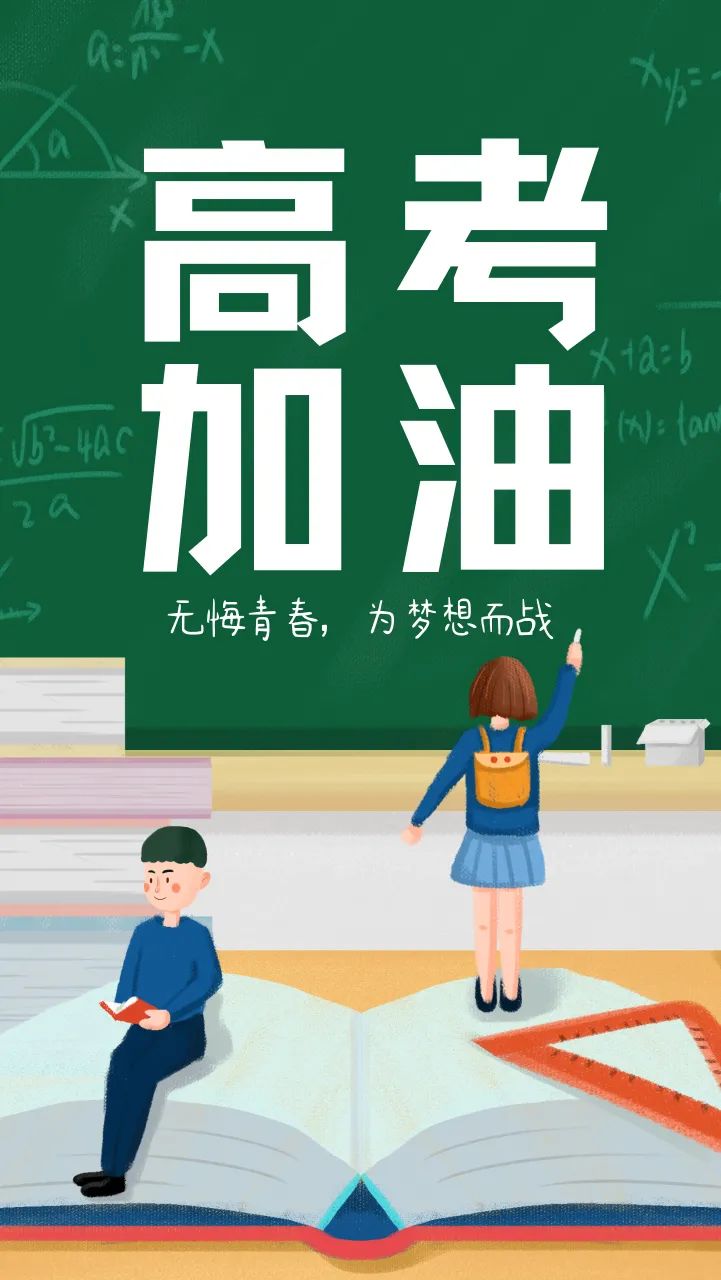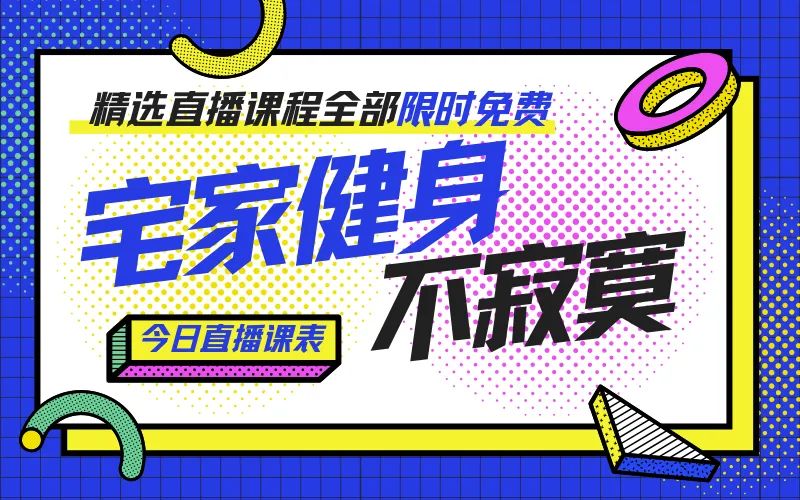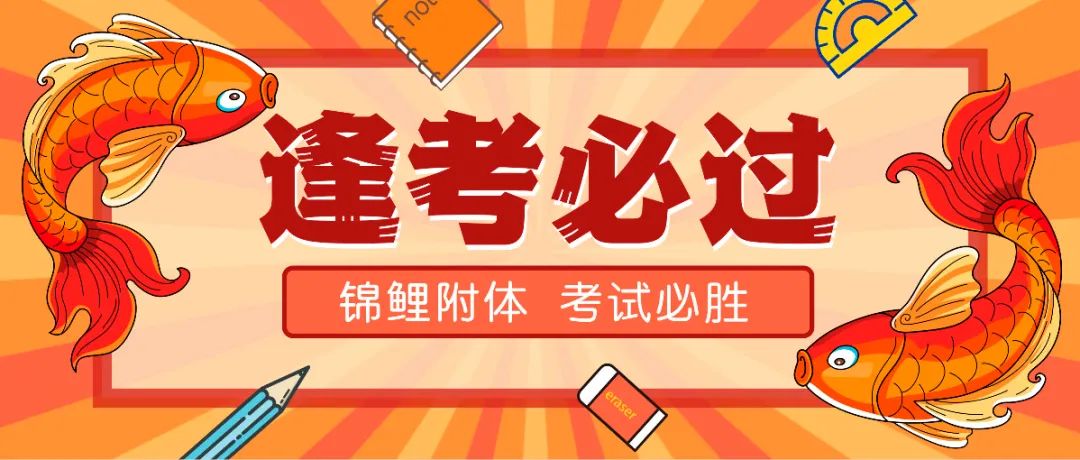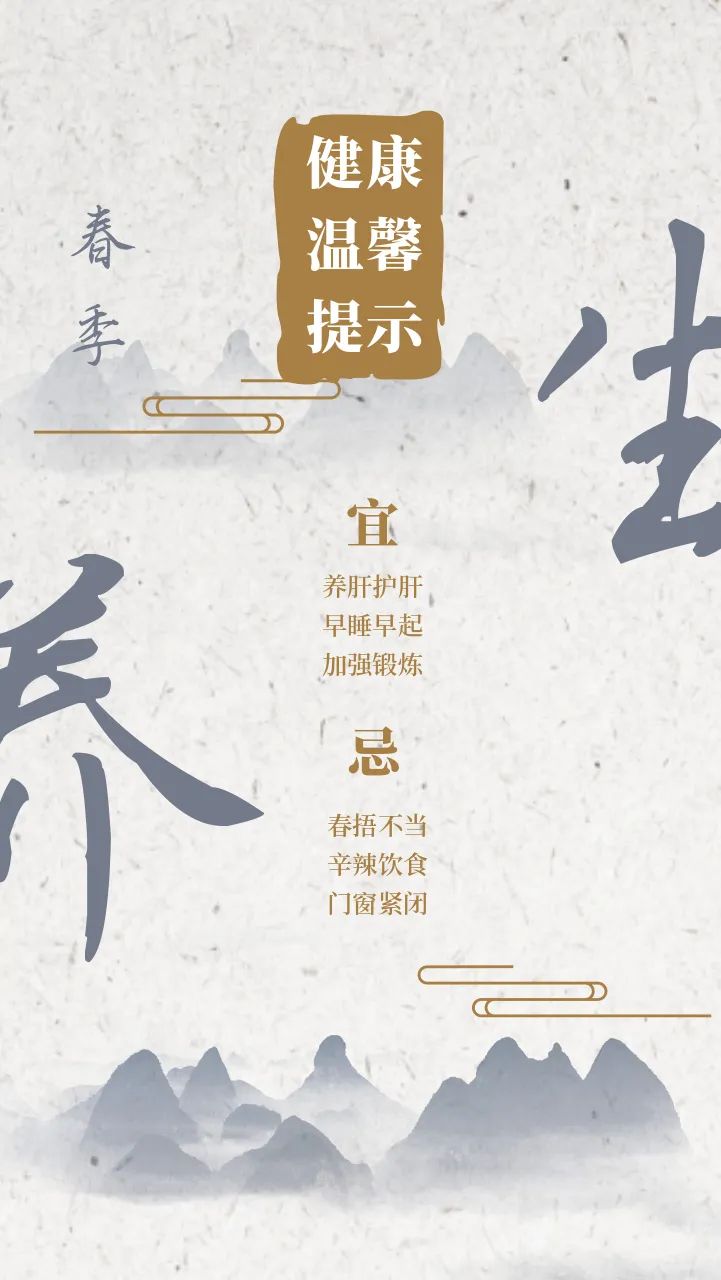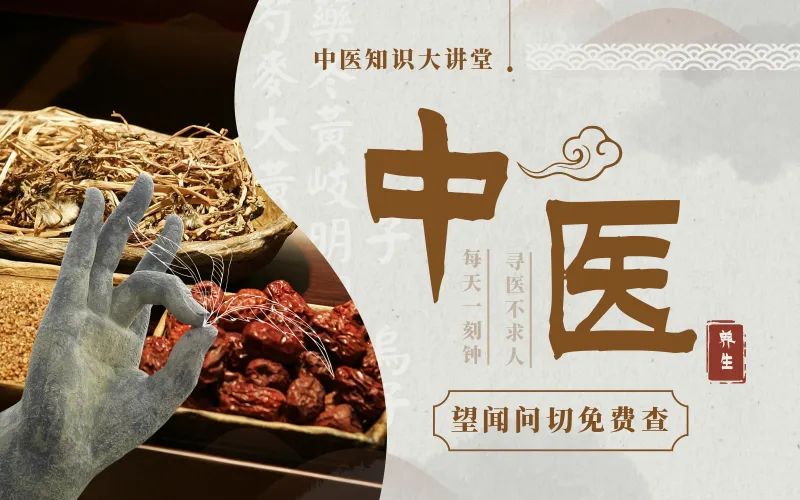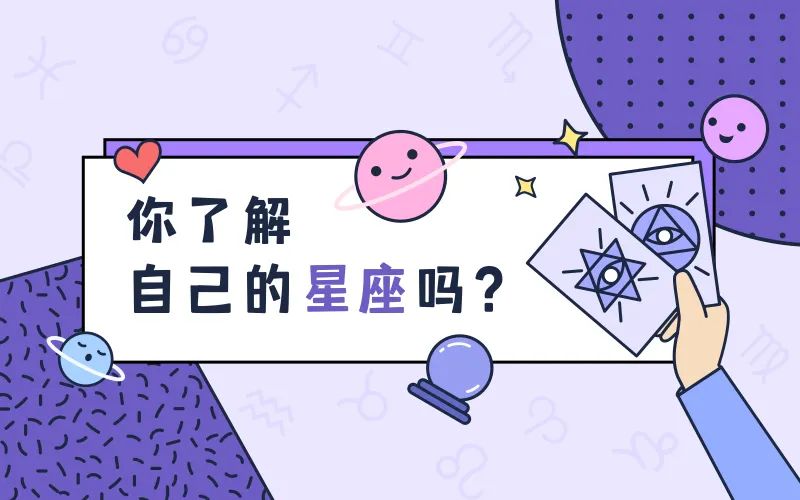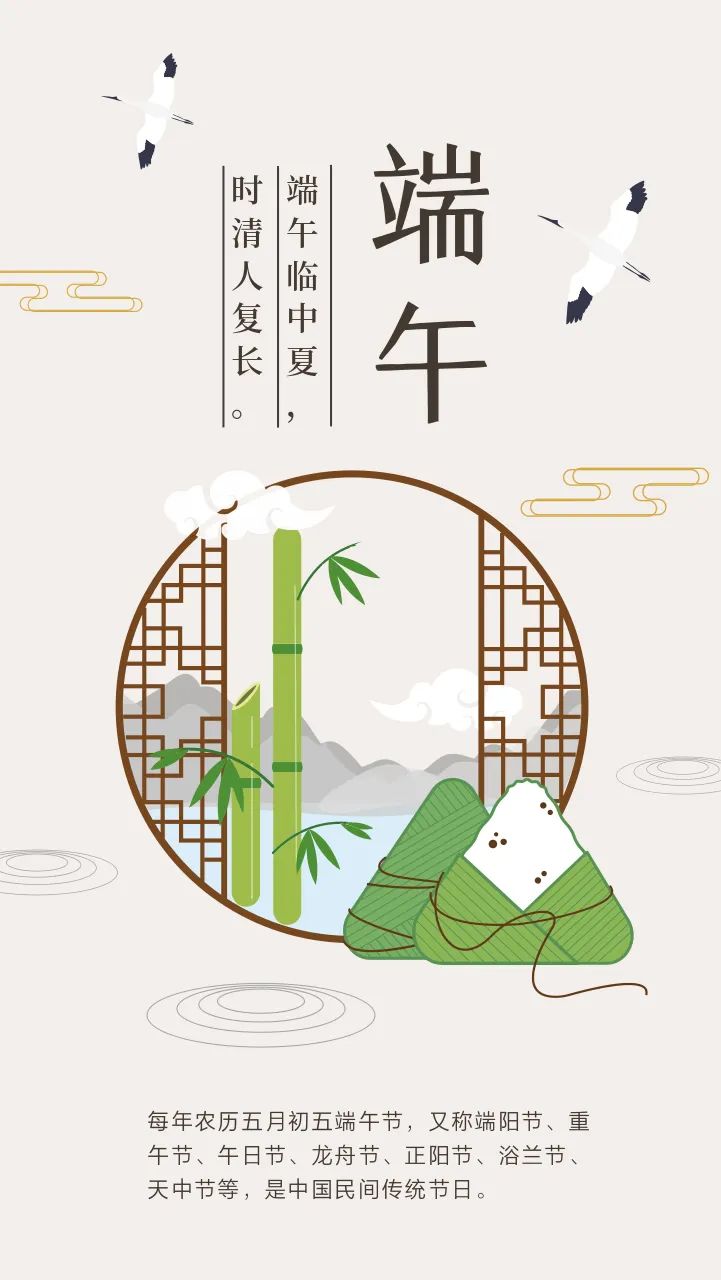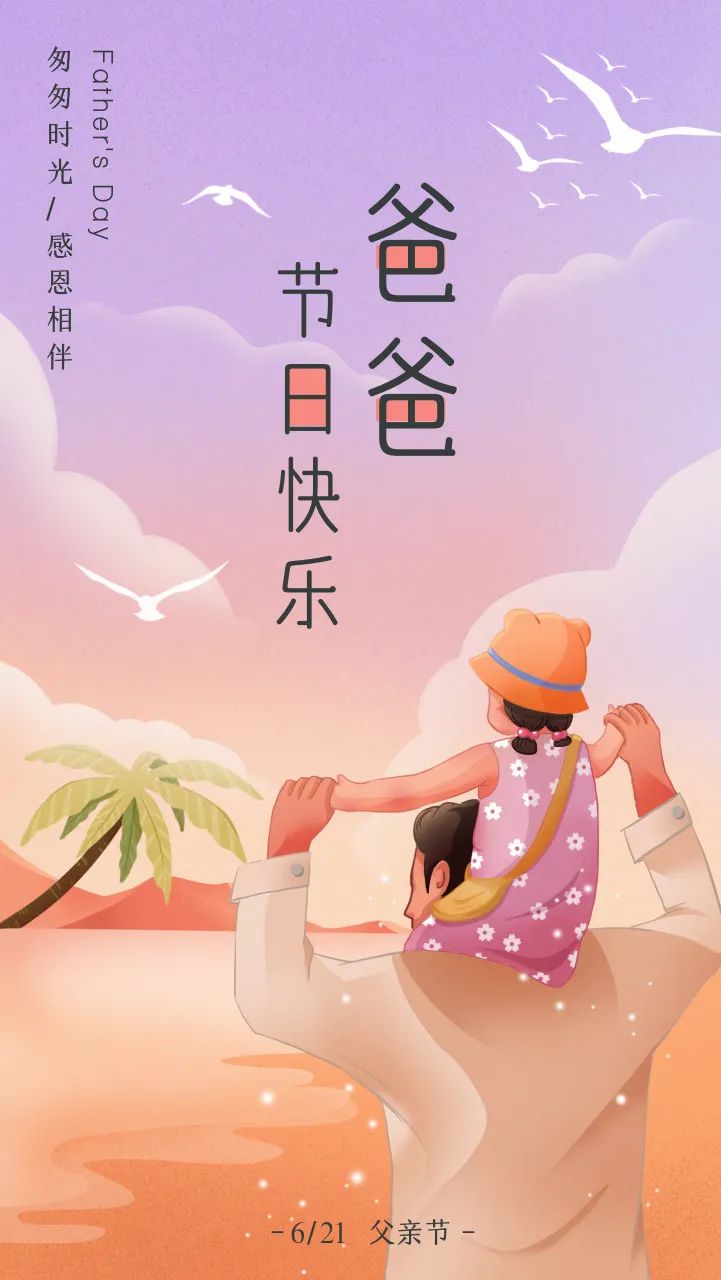
不下载字由,也可以使用会员字体,16款可商用字体分享
今天柚子要跟你说个好消息,懒设计正式上线了字由的16款可商用字体!
这意味着以后你可以直接在模板中使用字由的会员字,而无需下载客户端了。
那此次都有哪些字体上线呢,听柚子给你娓娓道来~
醒目装饰体
又粗又吸睛的装饰体,一定是海报中必不可少的,所以点字简宋、点字倔强黑、点字江户招牌黑、字由文艺黑来啦!
多变手写体
手写体风格多变,每一款都有其自身的气质,所以字由特意精选了点字春意体、点字手写漆书、点字手写童真体、点字浅夏体。
百搭女性字
作为电商的第一大主力军,时尚、复古、软萌的女性字体,总是能带来满满的好感,而点字美玲体、点字匹喏曹、点字奇妙体、点字乐圆体、字由芳华体,正是如此对味~
经典文化字
如果你经常要做节日的借势海报,肯定会用到点字刻宋、点字淡墨行楷,自带一种历史的高级感和传统的底蕴感。
完整的上线字体列表都在这了,你可以根据模板,选出最适合的字体,轻松做图。